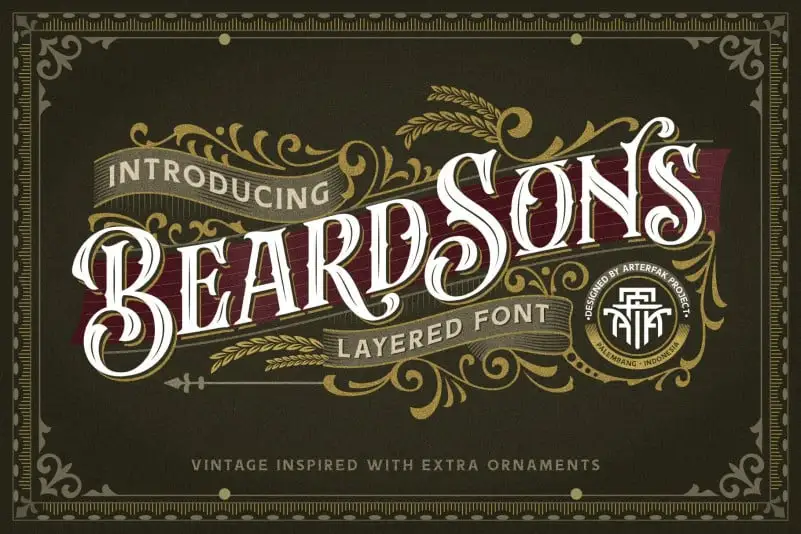
Beardsons Normal Blackletter Font – Download Grátis
Através do designer 99designs, Arterfak apresenta a ‘Beardsons Normal Blackletter Font’, uma tipografia robusta e elegante criada com um toque único: Normal – Inline – Shadow. Esta fonte é não apenas uma combinação de linhas grossas e textura característica da Blackletter, mas também traz à vida através do formato que oferece uma sensação de profundidade. Construída a partir de várias referências, como rótulos vintage, logotipos, emblemas e gráficos antiquados, a ‘Beardsons Normal Blackletter Font’ é perfeitamente adaptada para qualquer aplicação onde deseje destacar o estilo. Esta é uma fonte todo em caixa alta, cuidadosamente criada com um toque de decoração impecável que cria um ambiente sofisticado e elegante. Seja para gráficos publicitários ou logomarcas, a ‘Beardsons Normal Blackletter Font’ traz à sua peça de trabalho uma aparência única, robusta e bem trabalhada. Traz consigo o espírito vintage mas não se limita apenas ao passado – sua elegância moderna permite que você utilize esta fonte em qualquer contexto atual sem perder seu charme histórico.